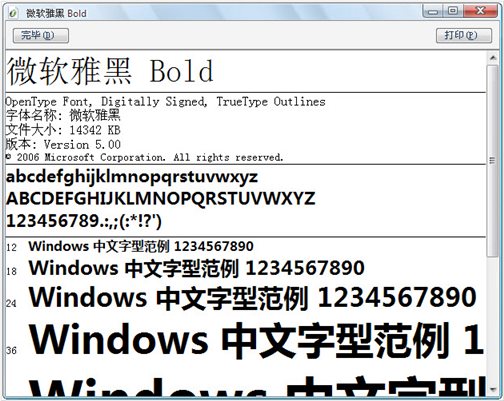
msyhbd.ttf是什么?msyhbd.ttf字體微軟雅黑粗體的英文縮寫,微軟雅黑可以說是目前應用最廣泛的字體之一了,筆畫清晰字形飽滿,非常容易識別,需要的朋友快來綠色資源網下載吧!
msyhbd字體介紹
雅黑,又稱微軟雅黑,是微軟公司為其新一代操作系統(tǒng)Vista開發(fā)的中文字體,它是迄今為止個人電腦上可以顯示的最清晰的中文字體。
微軟雅黑Bold這個粗體不是單純的將普通字符加粗,而是在具體筆畫上分別進行處理,因此是獨立的一個字體。